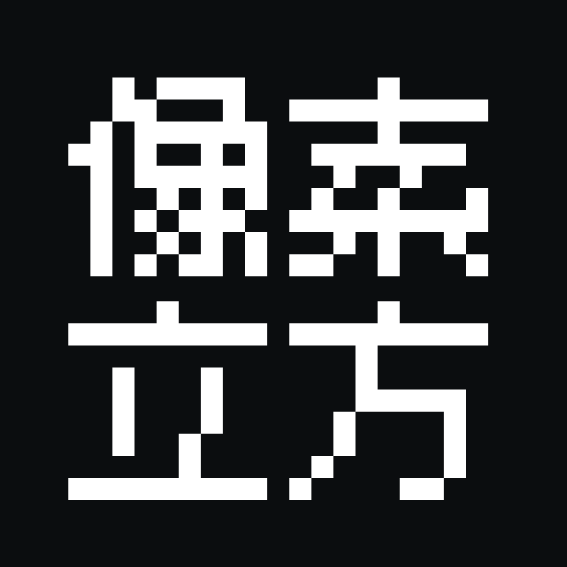
Pixel Font (chinese)
Обновлённый китайский пиксельный шрифт для Майнкрафт. Использует Cubic 11 для иероглифов и Compact Font для латиницы, идеально сочетается с ванильным стилем Minecraft Seven.
Обновлённый китайский пиксельный шрифт
Pixel Font (chinese) - это ресурспак для Майнкрафт, который полностью перерабатывает отображение китайских символов в игре. Вместо размытых или непиксельных шрифтов, которые по умолчанию используются в Minecraft для иероглифов, этот текстурпак ставит настоящий пиксельный шрифт Cubic 11. Он идеально вписывается в стилистику ванильного шрифта Minecraft Seven - того самого, что мы видим в интерфейсе, чате и на табличках.
Для английских символов используется Compact Font от Kaiji-Kun - он тоже сделан под пиксельную эстетику и не выбивается из общего вида. В итоге весь текст в игре - и китайский, и английский - смотрится единообразно и аккуратно.
По факту, если вы играете на китайском языке или используете моды с китайским текстом, стандартный рендер символов часто ломает атмосферу - буквы кажутся слишком мелкими или размытыми. Pixel Font решает эту проблему: иероглифы становятся чёткими, ровными и приятными глазу. Особенно это заметно в GUI, названиях предметов и книгах с пером.
Кстати, ресурспак поддерживает и традиционную китайскую письменность (繁體中文) - так что подойдёт и тем, кто играет на тайваньском или гонконгском варианте.
• Cubic 11 - шрифт от ACh-K.